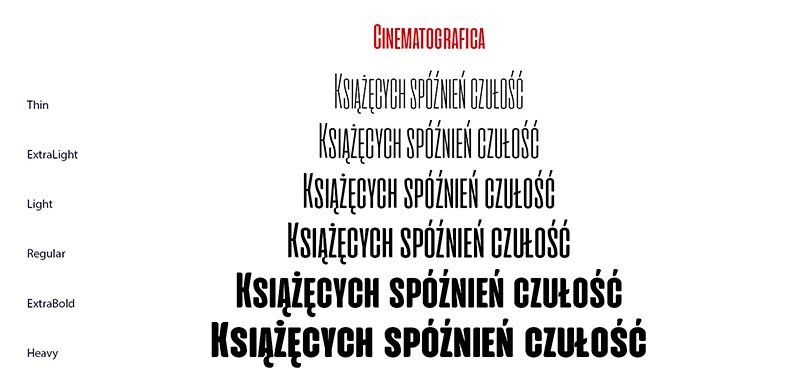
Font Cinematografica
Zakpiliśmy mocno skondensowany font nagłówkowy Cinematografica. Zanjdzie zastosowanie przy projektowanych przez nas kolorowych magazynach.